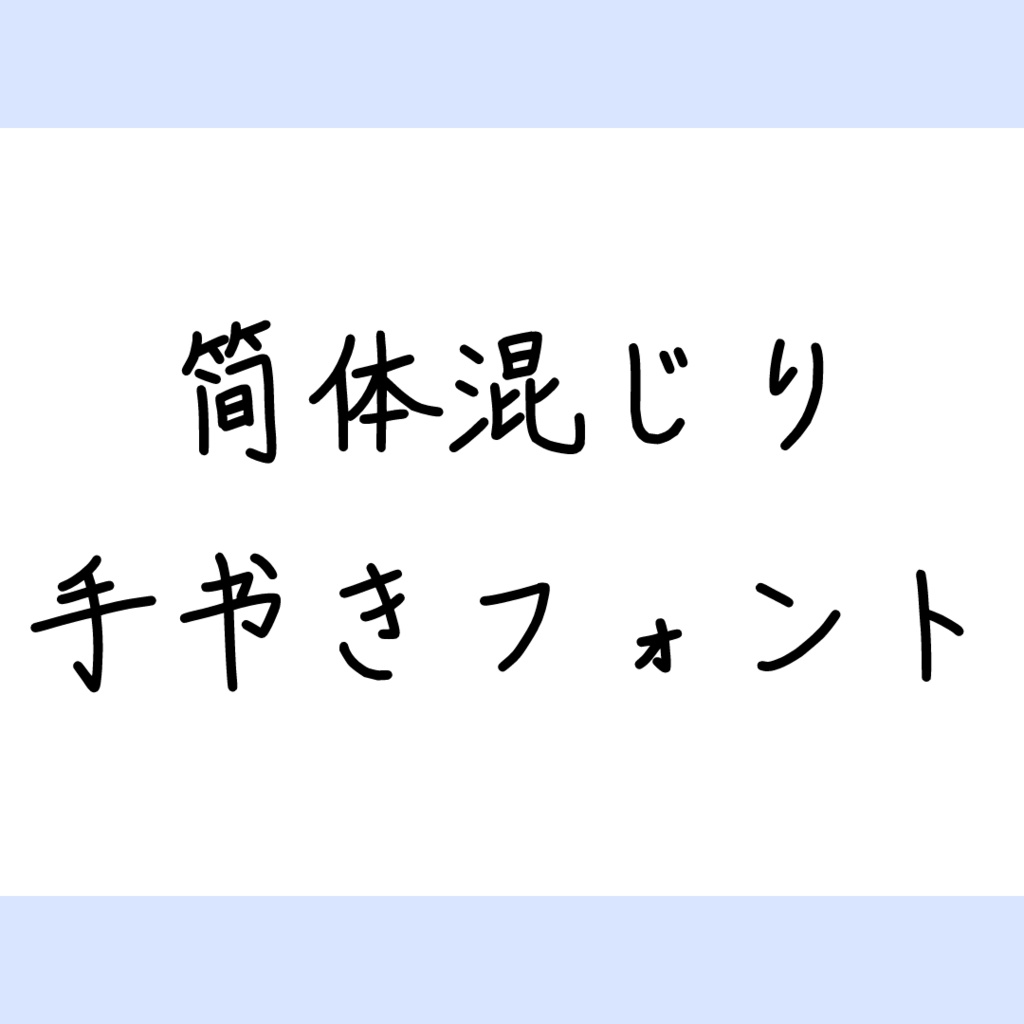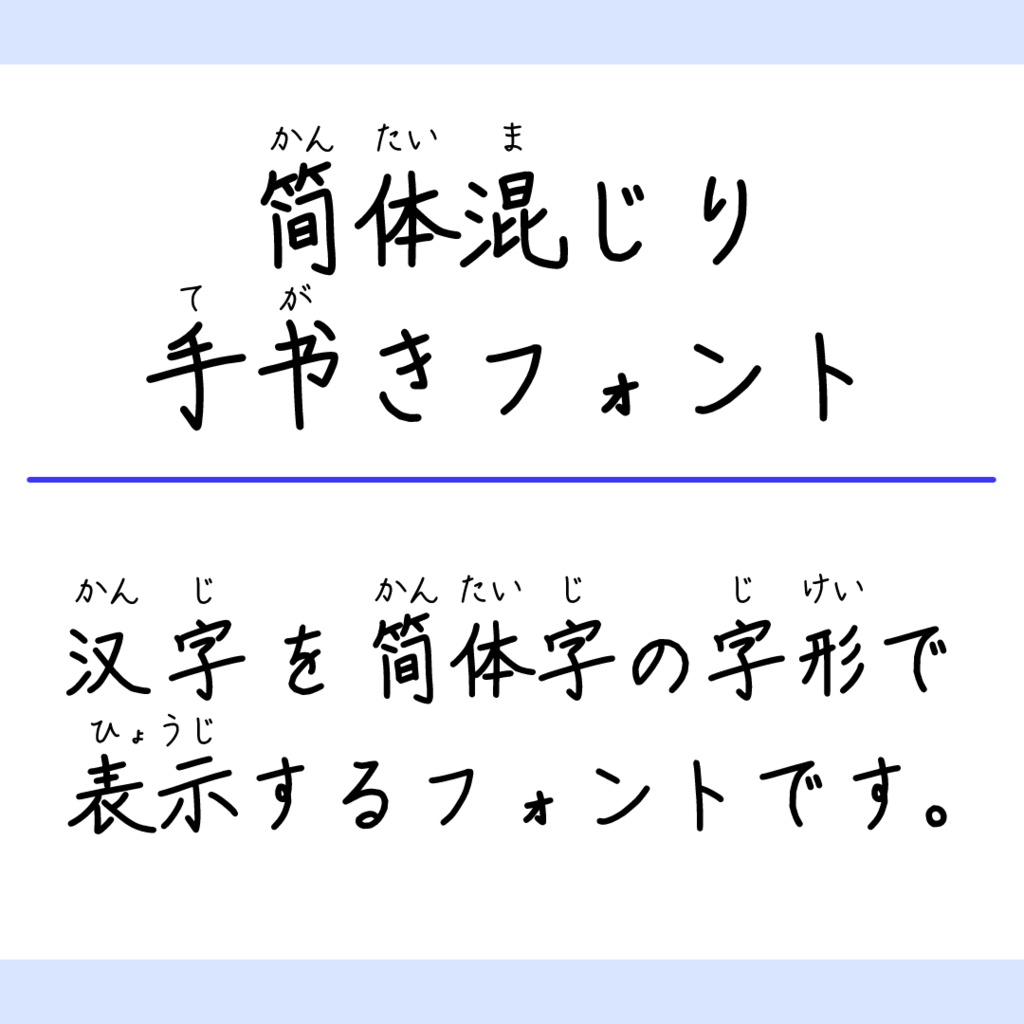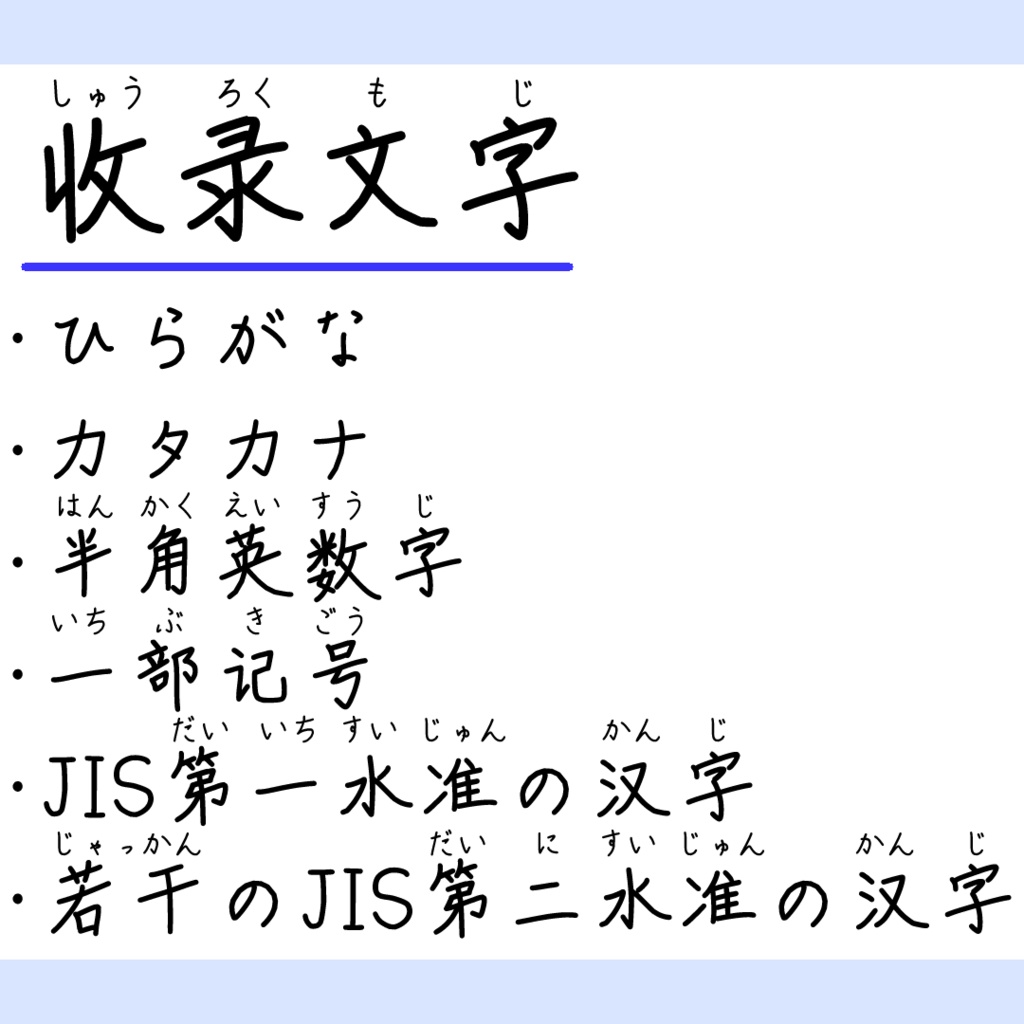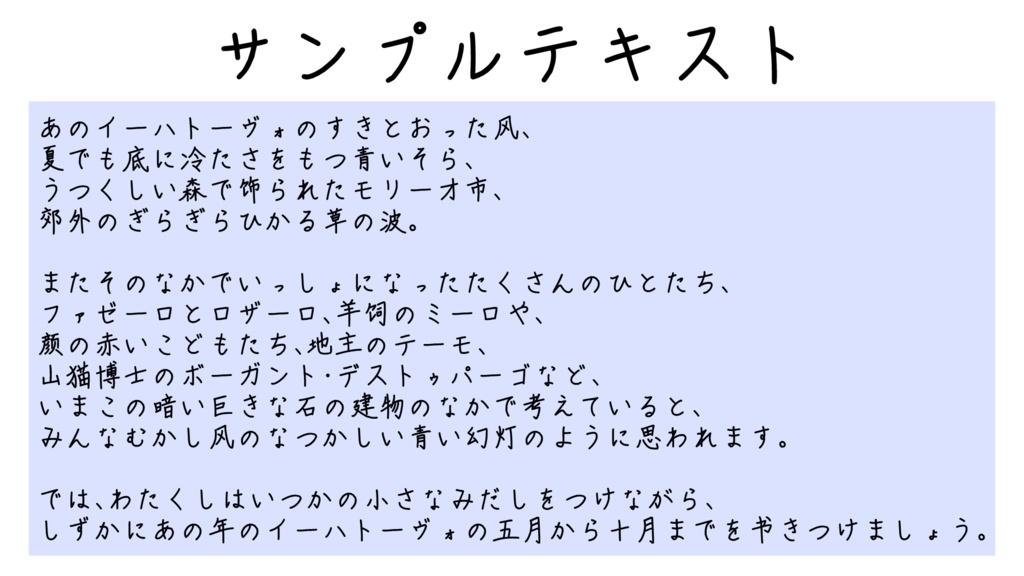
【フリーフォント】簡体混じり手書きフォント
漢字に、主に中華人民共和国で使用されている「簡体字」の字形を取り入れた手書きフォントです。 趣味で作成したフォントであるため、文字にがたつきがあったり、文字ごとの大きさのバランスが取れていなかったりする場合があります。あらかじめご了承ください。 ひらがな・カタカナ・半角英数字・一部の記号・JIS第一水準の漢字、および一部のJIS第二水準の漢字を収録しています。 簡体字には、複数の漢字が一つの漢字に統合されているものがあります。そのため、本フォントを用いて漢字を入力すると、入力した漢字とは異なる漢字が表示される場合があります。 また、上記の理由とは別に、単純な書き間違いによって誤った漢字が表示される場合もあるかもしれません。見つけ次第、ご報告いただけますと幸いです。 当フォントは、ばっと様による以下のツールを使用して作成しました。心より御礼申し上げます。 https://buttaiwan.github.io/writemyfont/ja.html 【利用規約】 ・商用・非商用を問わず利用可能です。 ・変形・加工可能です。 ・著作権は放棄していません。 ・このフォントを使用したことによるトラブル、不利益には一切の責任を負いません。 ・予告なく内容を変更、または公開を終了する場合があります。